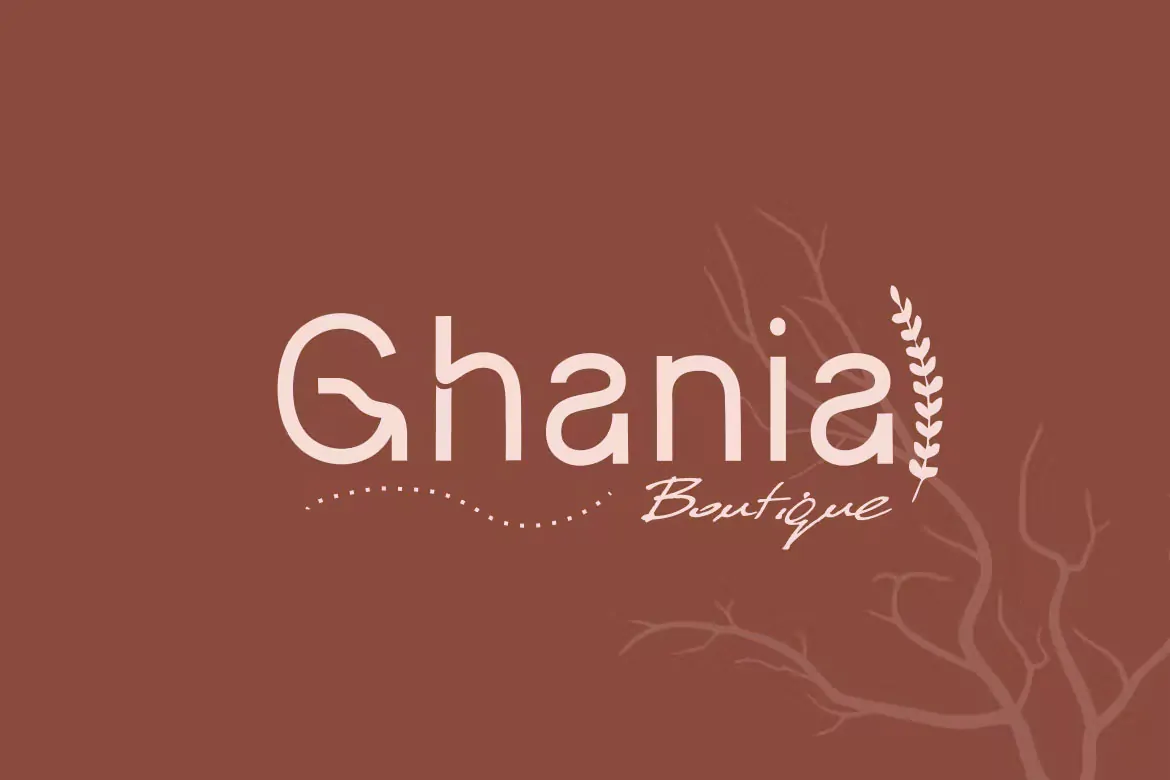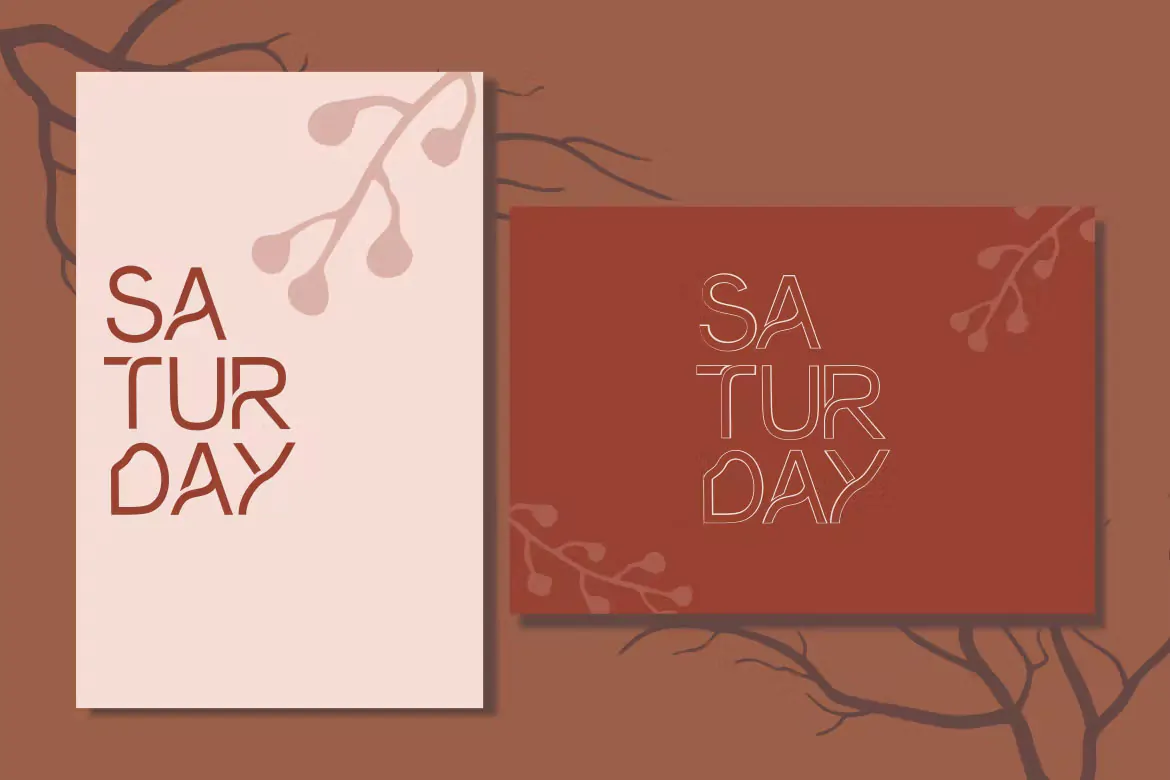
فونت تزئینی OBSTAC
فونت تزئینی OBSTAC یک قلم فوق العاده زیبای انگلیسی است که مناسب برای استفاده در طرح و پروژههای مختلف همچون طراحی لوگو، کارت ویزیت، پوستر، بنر، بسته بندی محصولات و … میباشد.